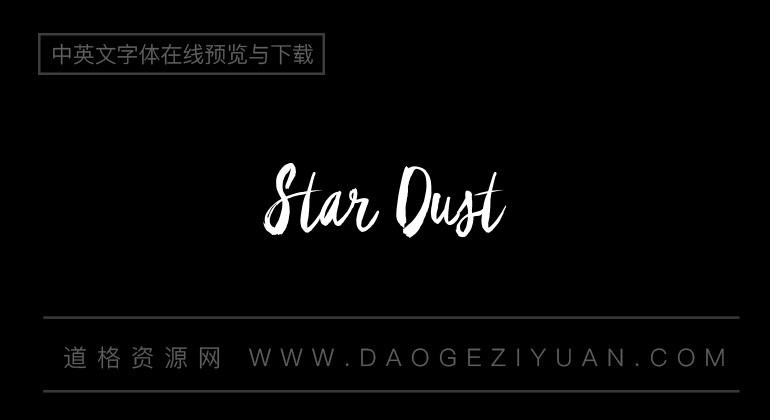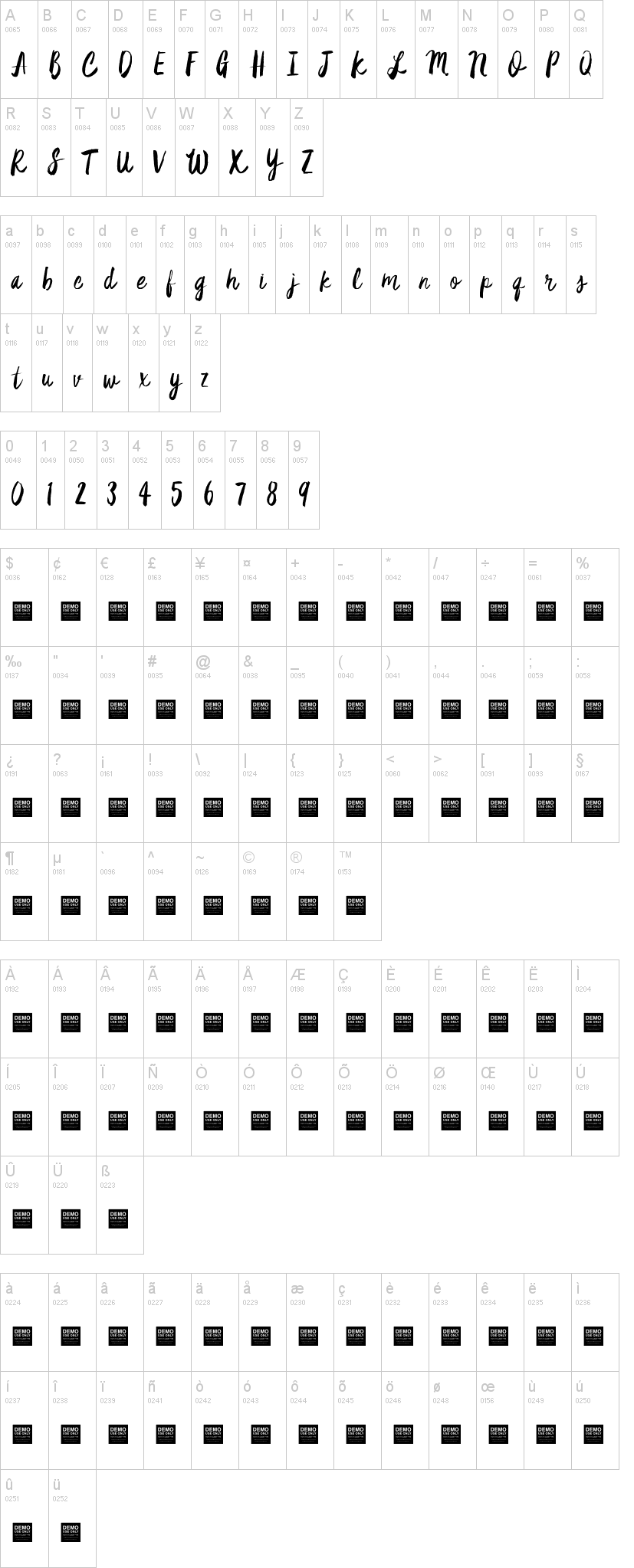
Star Dust 是一款经典的花体字体,它由著名的英国字体设计师Alfred Roller于1914年创作。该字体具有独特的风格,其字形具有强烈的装饰性,充满了浪漫情怀。该字体被广泛应用于海报、书籍封面、礼品盒等,能够给视觉效果带来极大的美感。内容介绍
Star Dust是一款非常不错的手写艺术字体,具有很好的视觉感,适合于文化类的宣传设计、商业类品牌的广告和产品包装设计以及个性化文字排版等较多场景。